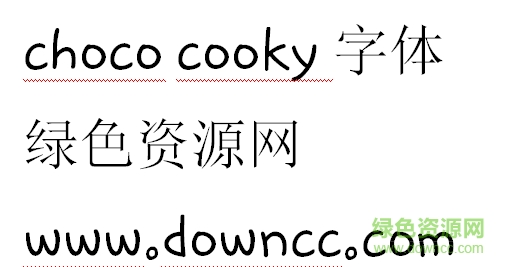
choco cooky ttf是一款造型充满童趣的艺术字体,圆润的外观的清晰的辨识度让你的阅读体验更加,无论是平面设计还是海报制作都很有特色,绿色资源网诚意推荐!
choco cooky字体,字迹简约清秀,充满孩子的天真活泼感,有着卡通字体的趣味,字体连贯不拖沓,给人舒适的视觉呈现,可运用于艺术创作、文字编辑、排版印刷等领域!